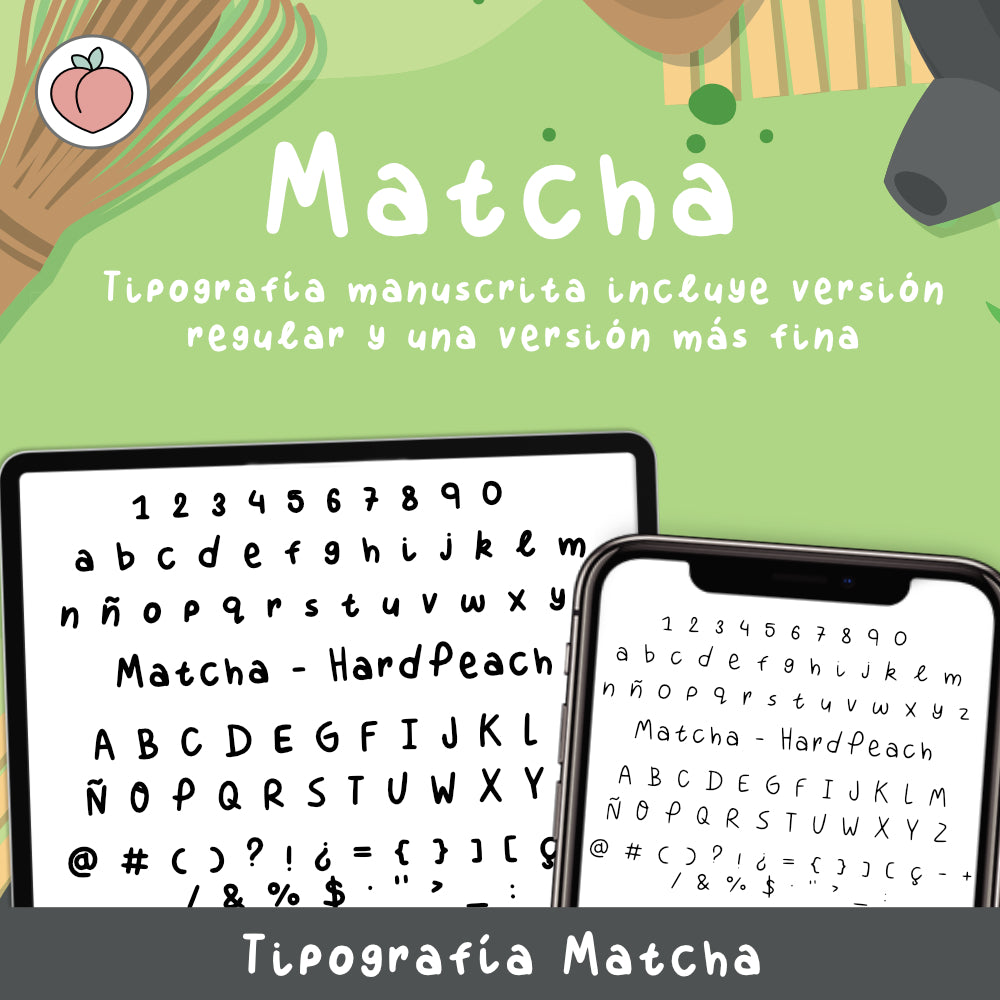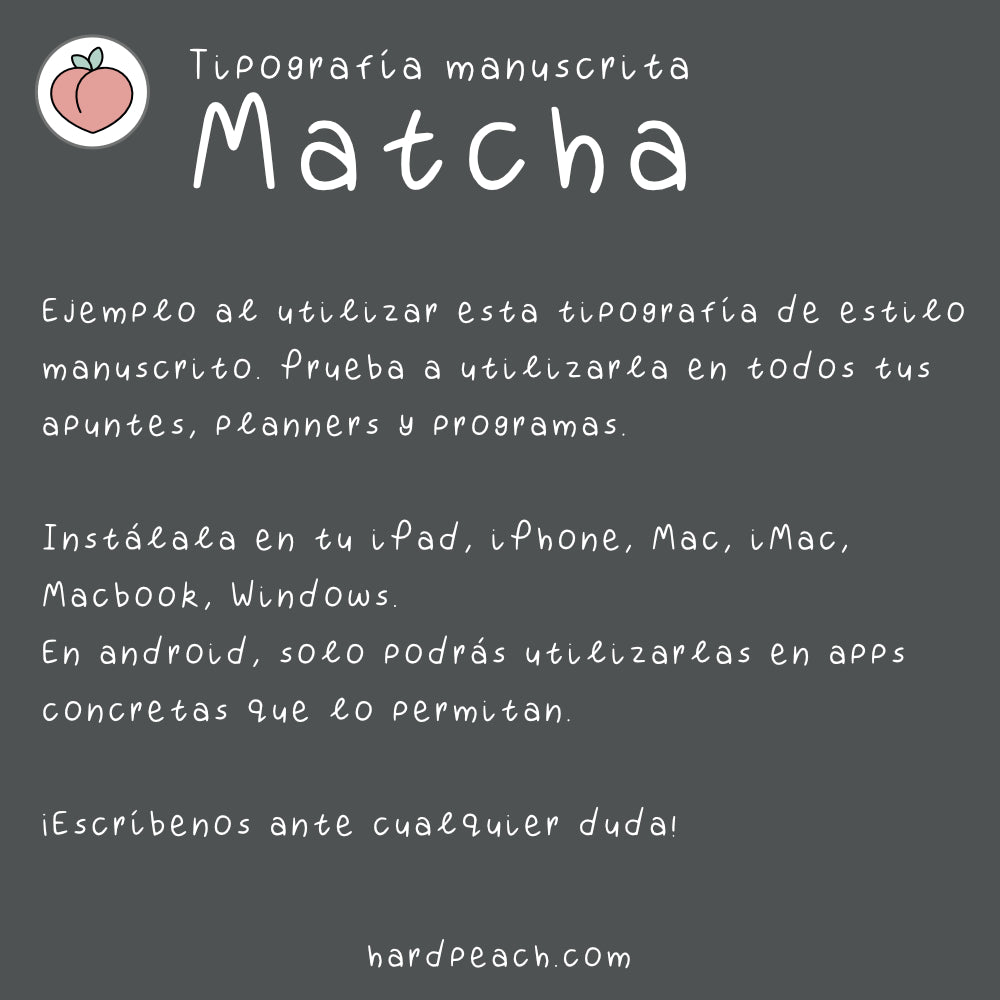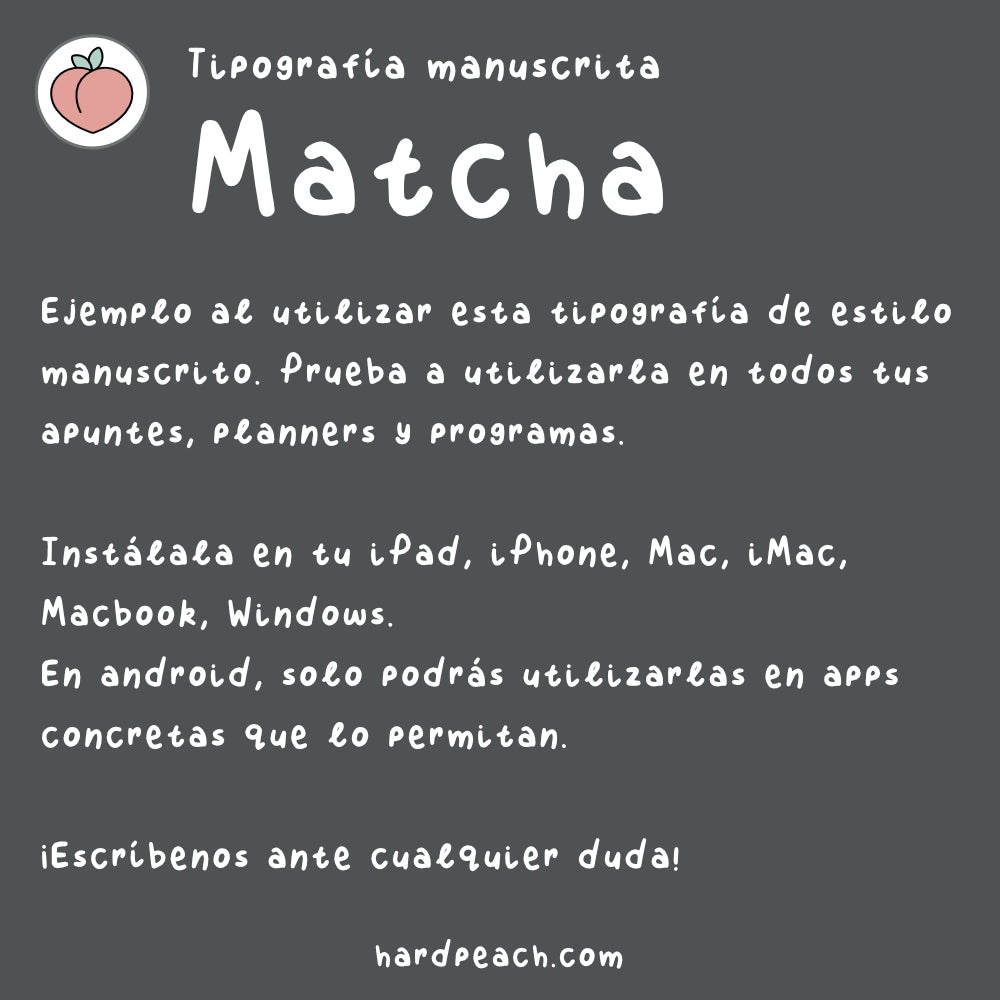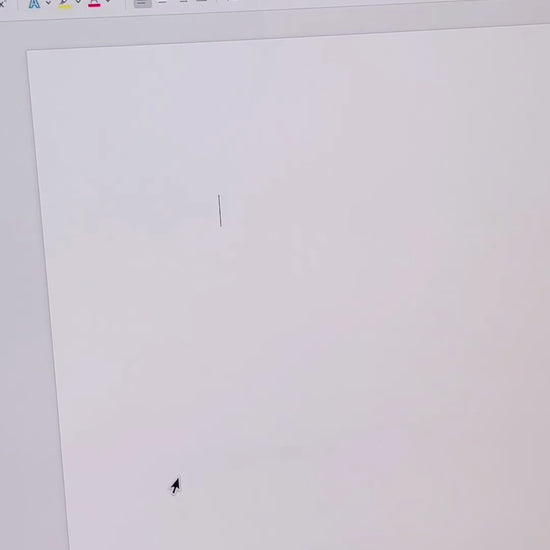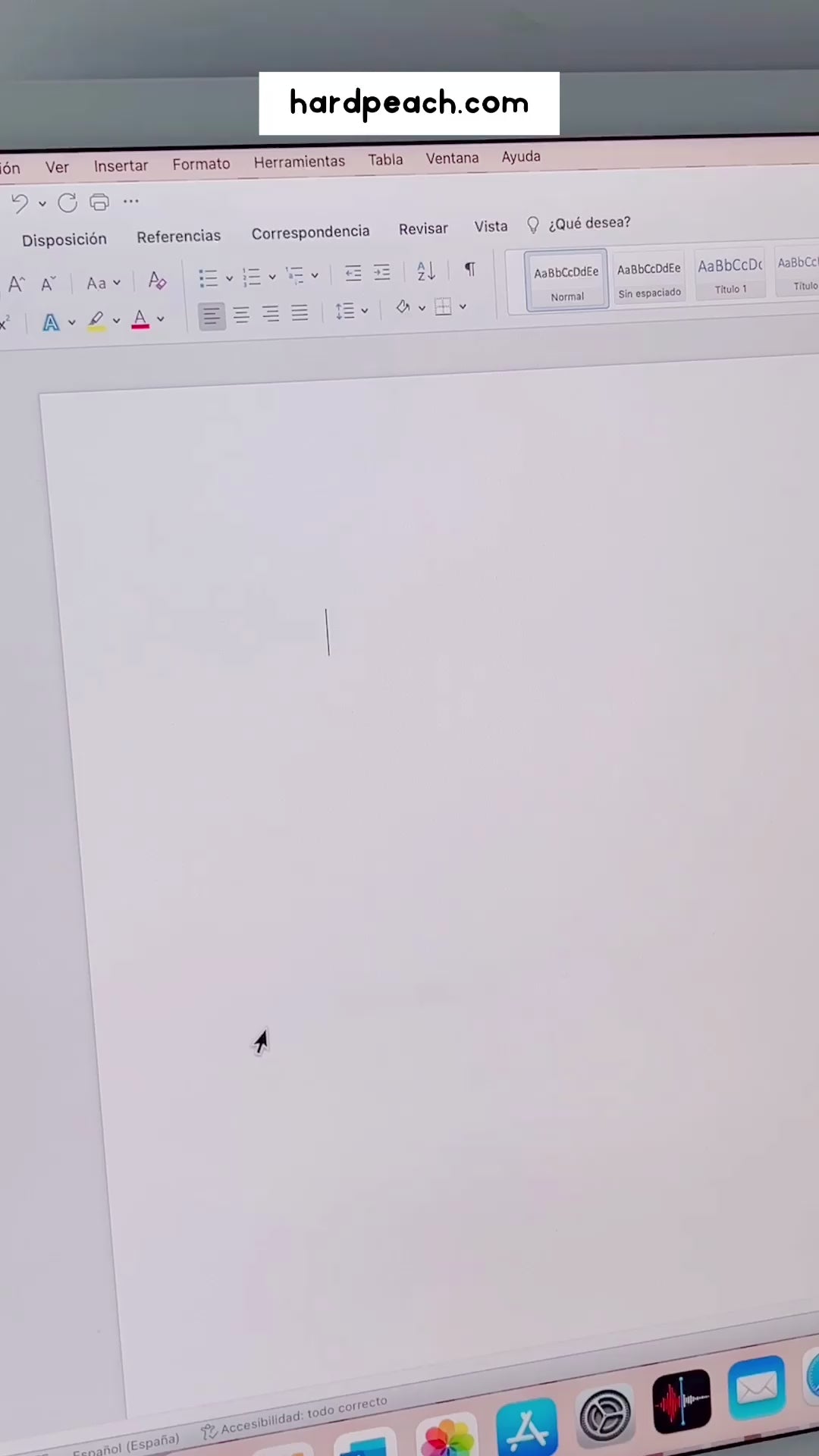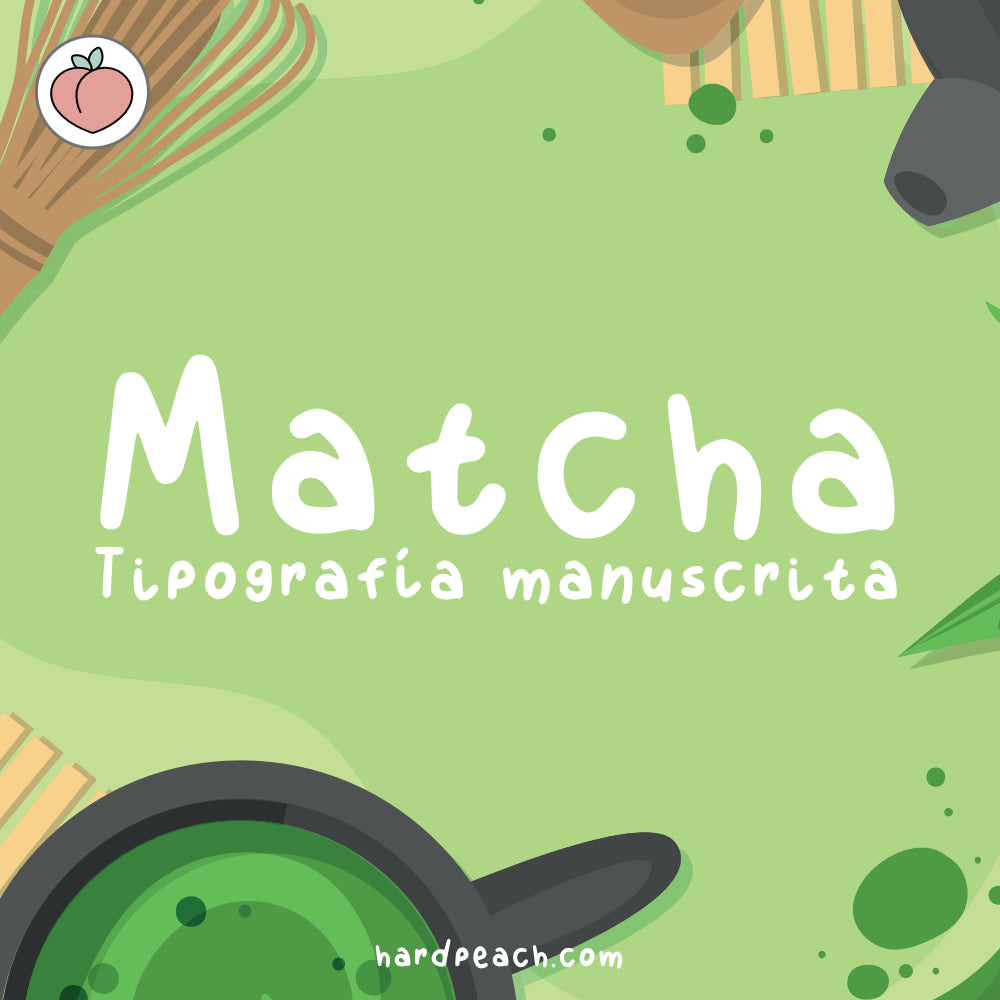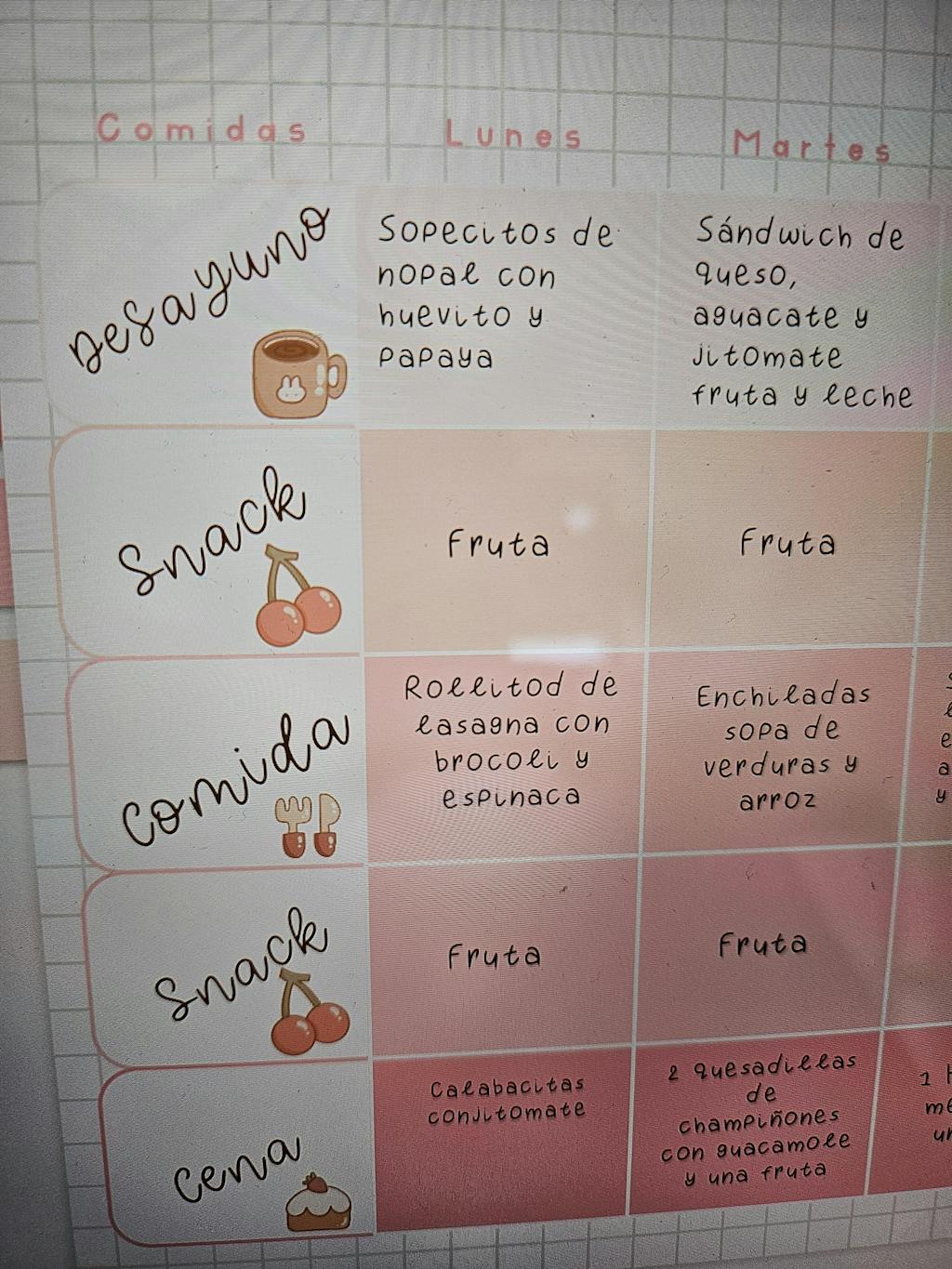
TIPOGRAFÍA MANUSCRITA MATCHA: Fuente escrita a mano para apuntes, notas, agendas y proyectos
Dale un toque único y personal a todos tus apuntes, notas, esquemas, agendas digitales, bullet journals, ilustraciones, proyectos escolares, trabajos creativos y cualquier diseño digital con la tipografía manuscrita Matcha. Esta fuente escrita a mano está diseñada para que tus textos tengan un estilo auténtico y hecho a mano, aportando personalidad y frescura a cada proyecto.
Incluye dos versiones de la tipografía: una más fina y elegante, y otra más gruesa y destacada, para que puedas adaptarla a cualquier tipo de uso o estilo visual. Es perfecta tanto para apuntes digitales organizados y bonitos, como para titulares creativos en presentaciones, ilustraciones, diseños gráficos o planners digitales, haciendo que tus contenidos se vean profesionales y con un toque personal.
Esta fuente también es ideal para:
- Apuntes escolares y universitarios digitales
- Bullet journals y agendas digitales
- Proyectos creativos y presentaciones
- Diseño de ilustraciones y lettering digital
- Creación de títulos y subtítulos con estilo manuscrito
- Notas personales y planners de organización
Además, incluye todos los caracteres principales: mayúsculas, minúsculas, números, vocales con tildes abiertas y cerradas, signos de puntuación y la letra Ç, asegurando compatibilidad con cualquier idioma o proyecto.
Esta tipografía incluye todos los caracteres principales, mayúsculas, minúsculas, números, vocales con tildes cerradas y abiertas y signos. Además de la letra Ç
Me gusta mucho como se ve, en la foto usé la variante regular, luego hay otra versión más fina, personalmente me gusta más la versión gruesa.
me ha gustado mucho para apuntes
la uso en apuntes
tiene la letra Ñ y eso me ha gustado
tipografia para apuntes como si se escribiera a mano
parece que estoy escribiendo a mano en el word jajaja me ha gustado